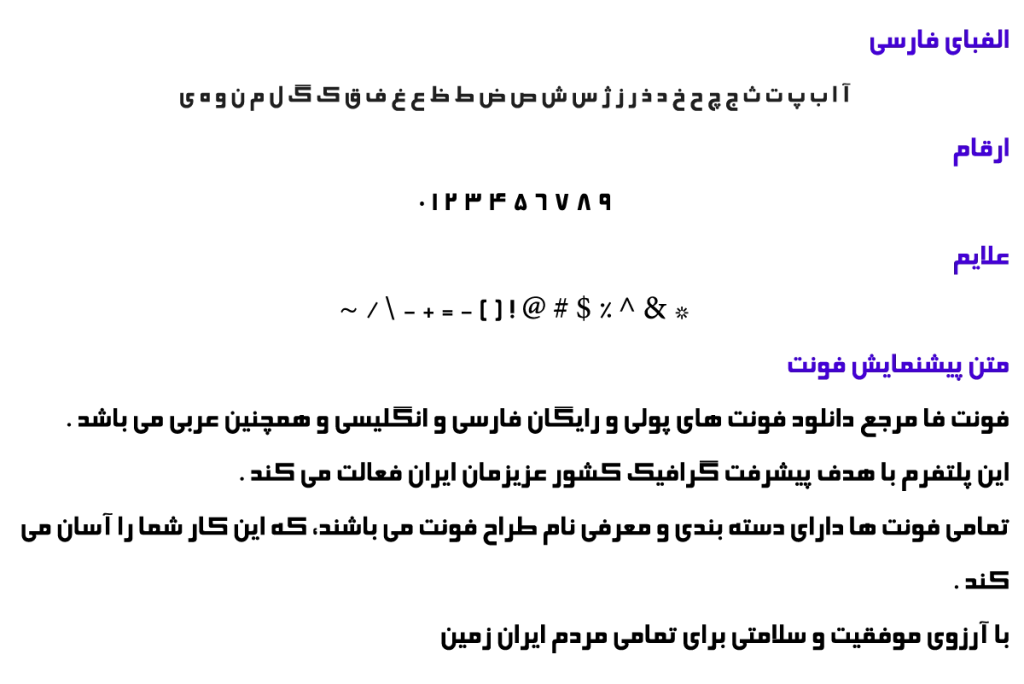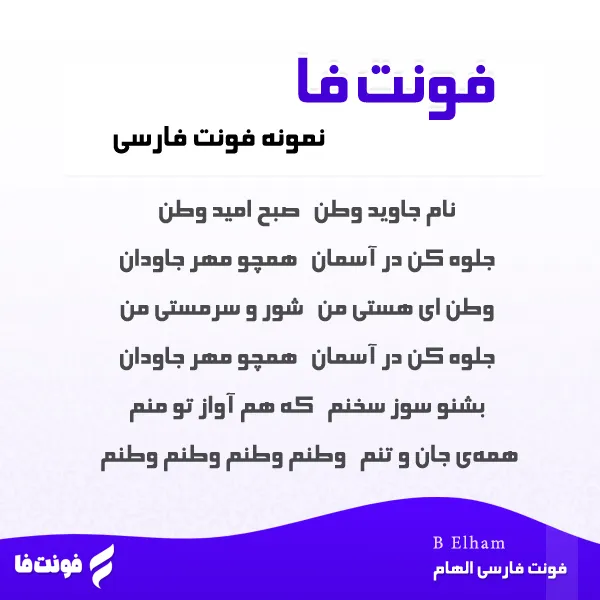
فونت فارسی الهام – B Elham
طراح فونت: برنا رایانه نوع فونت: فونت عنوان و فونت هندسی
پیشنمایش فونت الهام
توضیحات و معرفی فونت الهام
فونت فارسی الهام ( B Elham ) از مجموعه فونت های سری B می باشد، همینطور نوع فونت عنوان و هندسی می باشد.
فونت زیبای مرتبط توسط برنا رایانه طراحی و ساخته شده است.
همینطور فونت B Elham در یک وزن پر رنگ است.
- B Elham Bold
در تصویر زیر، شعر کهن «وطنم» با این تایپفیس به نمایش گذاشته شده است.